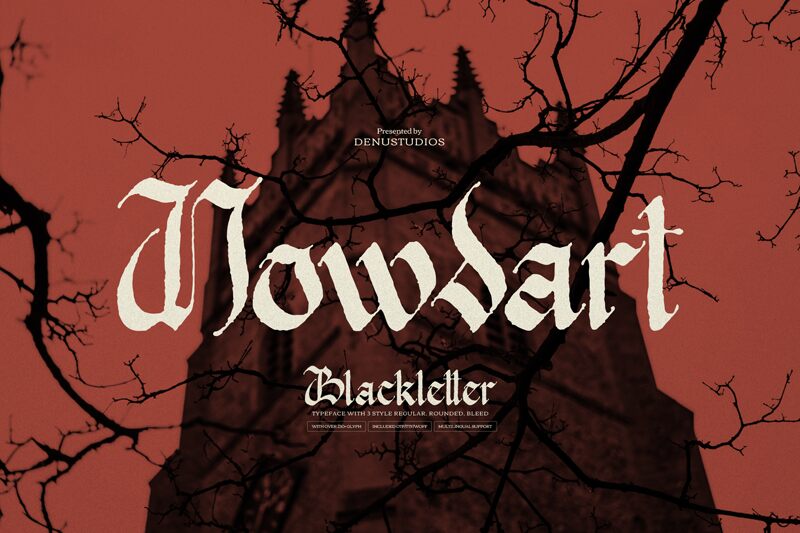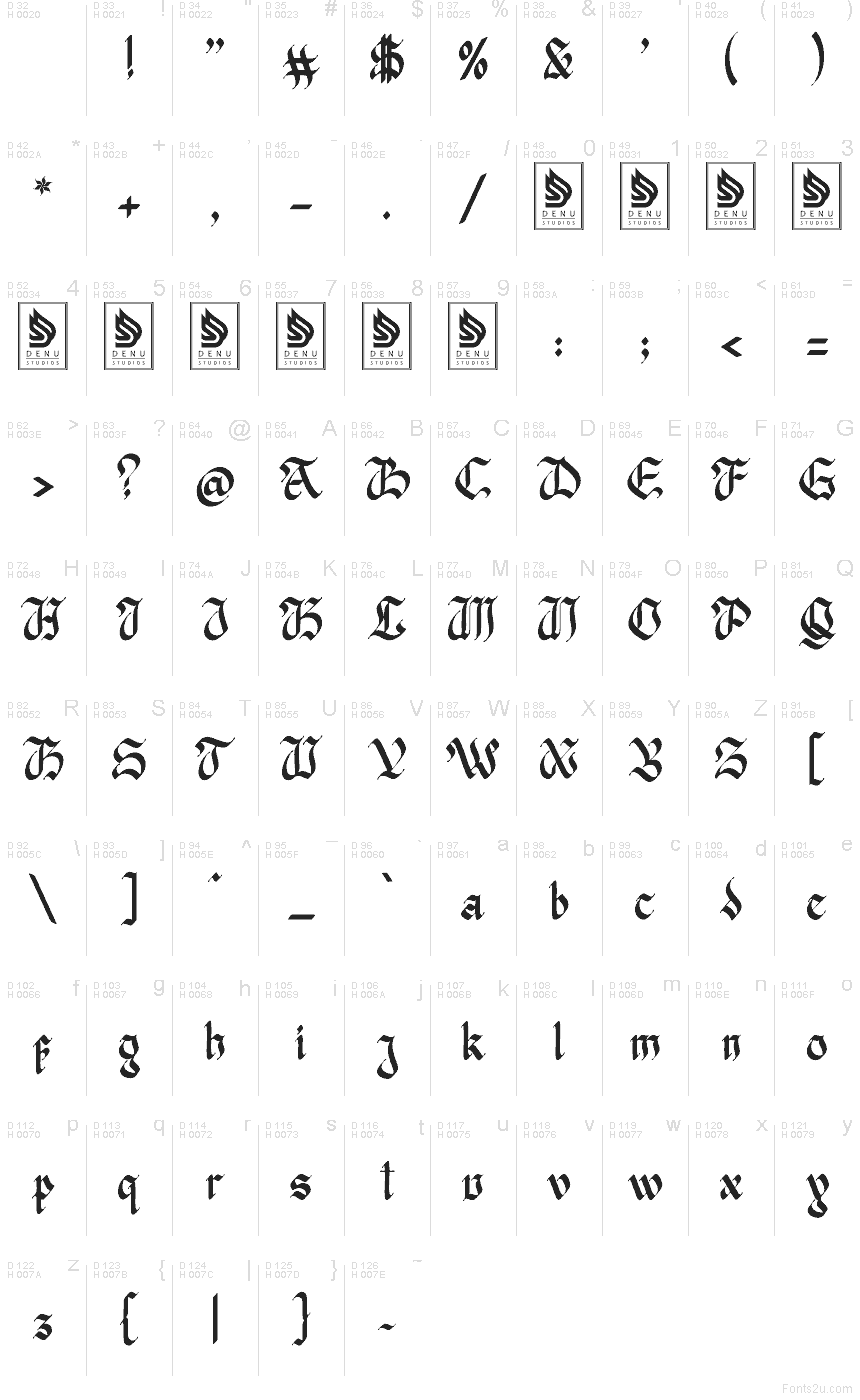
Nowdart Rounded od Denustudios je bezplatné, zaoblené stredoveké gotické písmo s jemnejším charakterom typu blackletter. Písmená si zachovávajú ostrý rytmus a dramatický vzhľad starých skriptov, ale vďaka plnším, priateľskejším krivkám, baňatým ťahom a zaobleným uhlom nepôsobia vôbec stroho.
Hodí sa na branding remeselných nápojov, tetovacích štúdií, herných titulov, hudobných plagátov, knižných obálok či merchandisingu všade tam, kde má bezplatné písmo evokovať heraldiku bez toho, aby pôsobilo archaicky. Použite ho na krátke nadpisy, logá, titulné karty alebo monogramy, pretože kombinácia ostrej dynamiky a zaobleného tvaru dodáva aj pár písmenám silný, emblémový vzhľad.
Nowdart Rounded